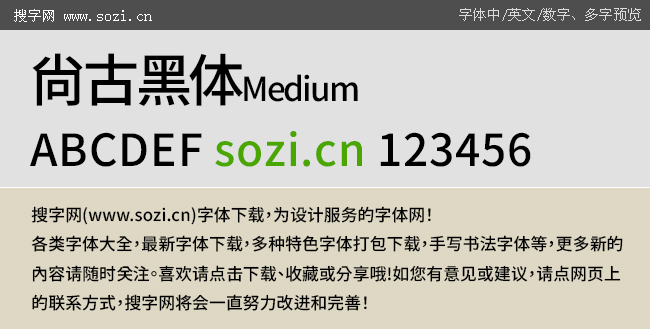
尚古黑體Medium
搜字網(wǎng)提供一款尚古黑體Medium中文字體下載,尚古字體是一套泛中日韓傳承字形(舊字形),基于思源黑體、思源宋體、思源等寬以及思源系列衍生字型制作,包含黑體、明體、圓體、等寬以及簡(jiǎn)轉(zhuǎn)繁字型。這款字體無(wú)論是個(gè)人還是企業(yè)都可以自由免費(fèi)商用,無(wú)需知會(huì)或者標(biāo)明原作者。適合包裝設(shè)計(jì)、海報(bào)設(shè)計(jì)、廣告設(shè)計(jì)等應(yīng)用。